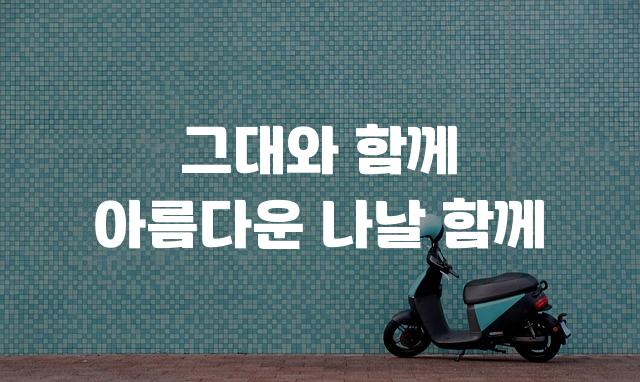
평택 반도체는 평택시청에서 제작된 현대적인 둥근 고딕 폰트로, 장식체의 특성을 지닌 독특한 디자인입니다. 이 폰트는 부드러운 곡선과 깔끔한 선으로 독자의 시선을 사로잡으며, 따뜻하면서도 전문적인 느낌을 줍니다.
평택 반도체은(는)
기본 고딕, 둥근 스타일, 장식 스타일, 감성적인, 부드러움, 복실복실, 별모양/패턴 계열의 생김새를 가지고 있으며
웹/앱 디자인, 보고서/문서 등에서 자주 활용되며, 효과적인 메시지 전달에 적합합니다.
이 폰트는 기술/IT, 금융/비즈니스 분야에 잘 어울리며,
명확한, 전문적인 느낌을 담고 있는 것이 특징입니다.